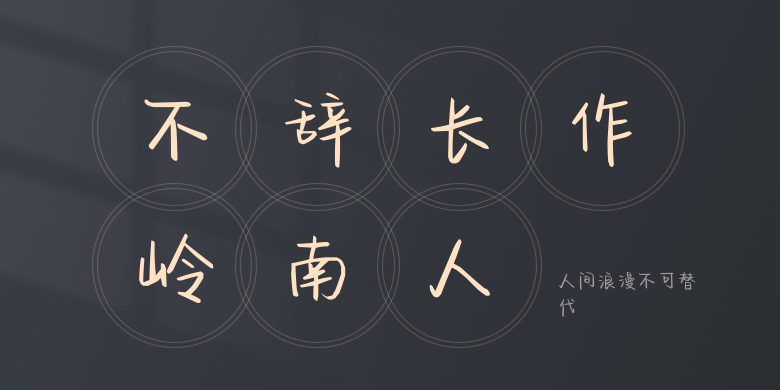
人间浪漫不可替代
人间浪漫不可替代,这款字体结构工整、笔画清晰,兼顾美观与易读性,适用于标题、正文、海报、包装、LOGO 等多种场景。字形优雅稳定,风格百搭耐看,适配日常排版与创意设计,让文字呈现更舒适、更具质感。人间浪漫不可替代一笔一画,皆是细节,以均衡的比例、流畅的线条打造舒适视觉体验,字形端正大气,风格简约现代。无论是商业设计、品牌宣传还是日常排版,都能轻松驾驭,让文字更有格调与力量。人间浪漫不可替代字体下载。